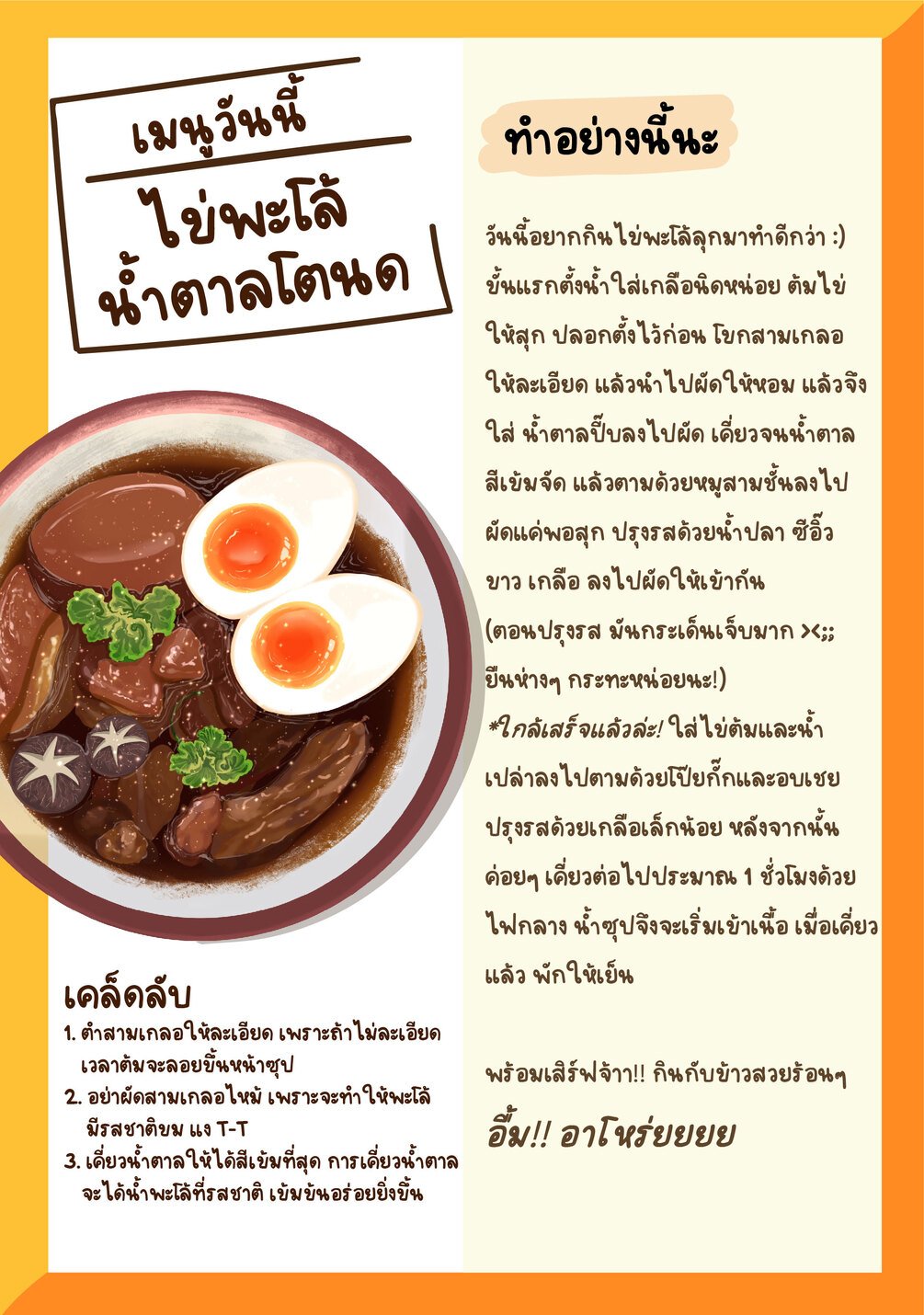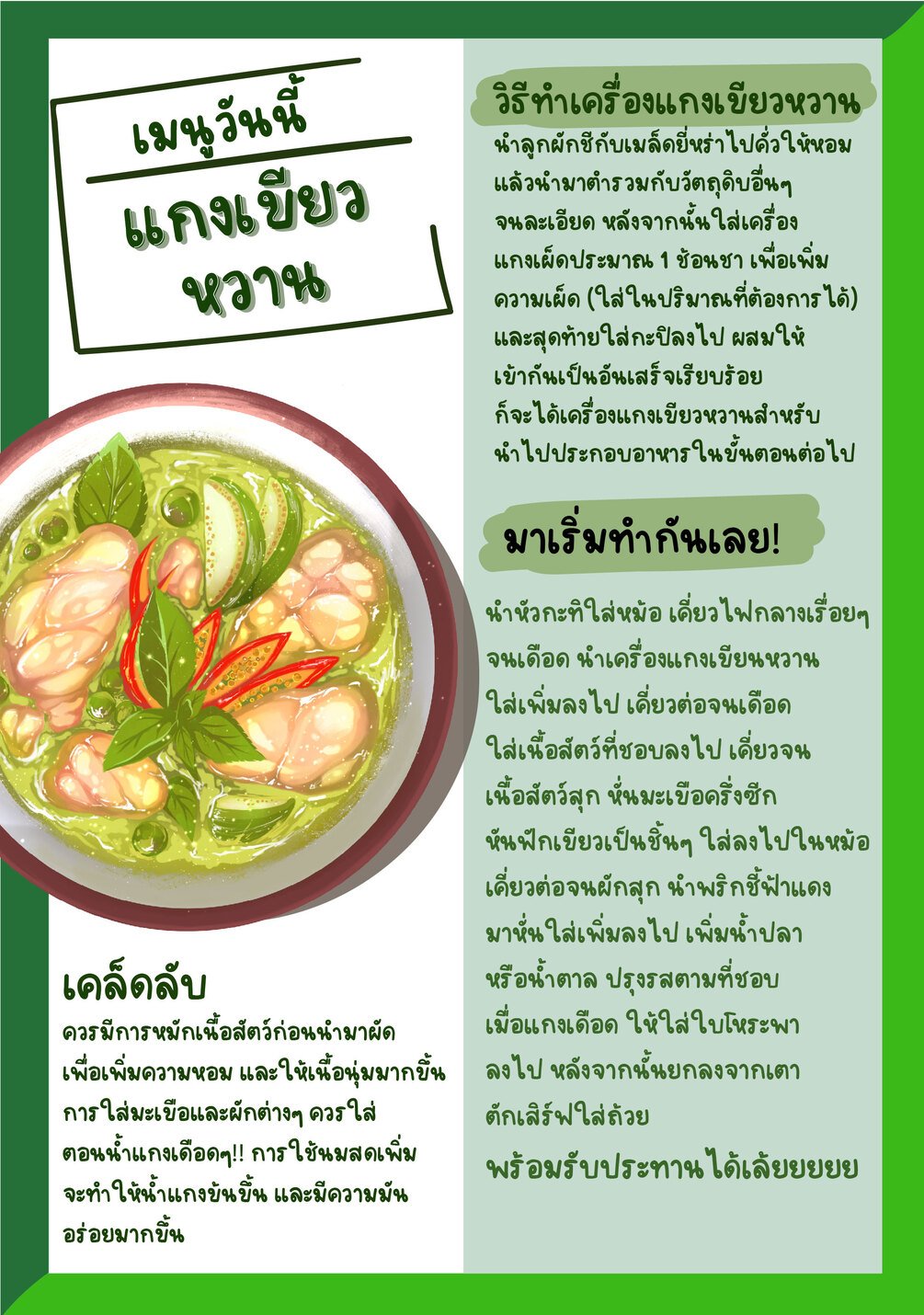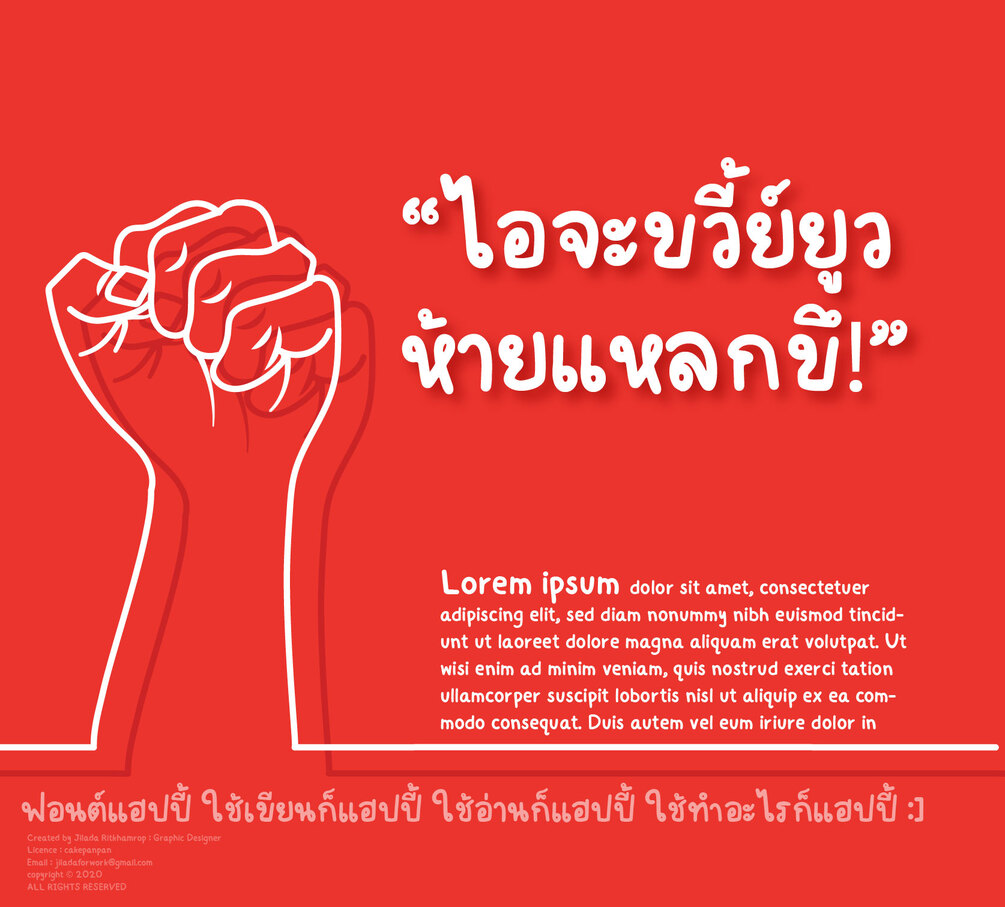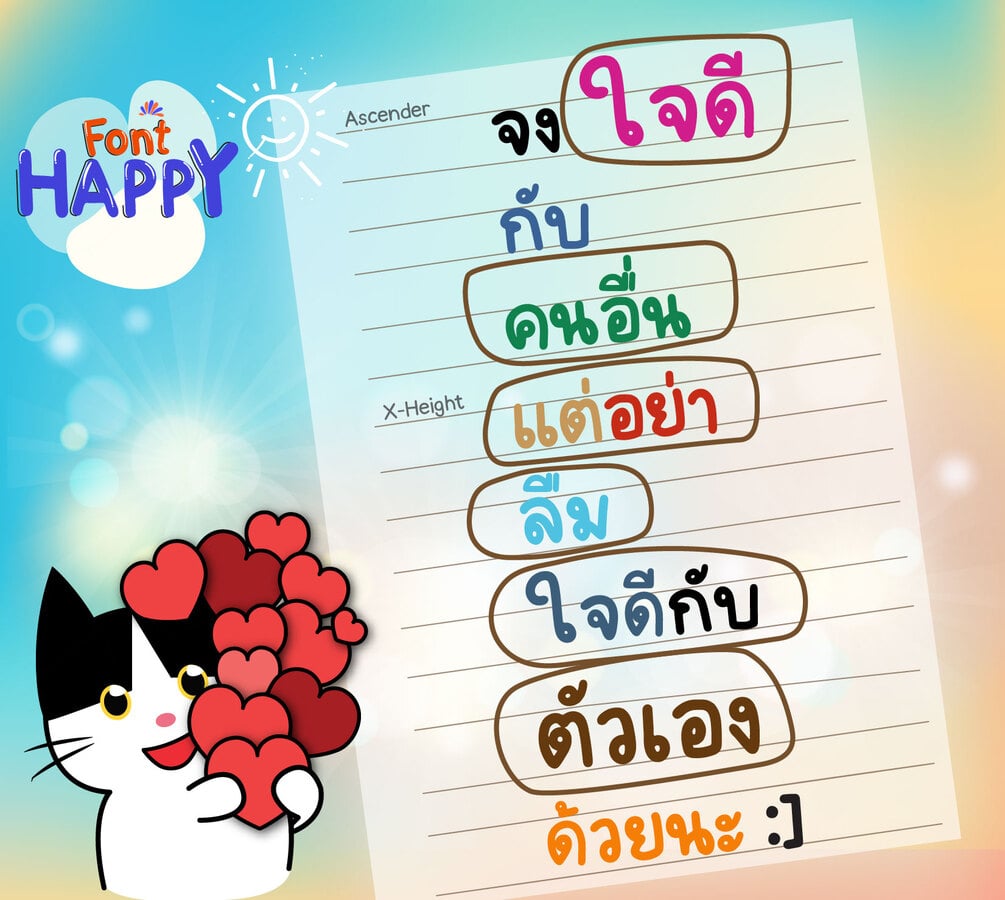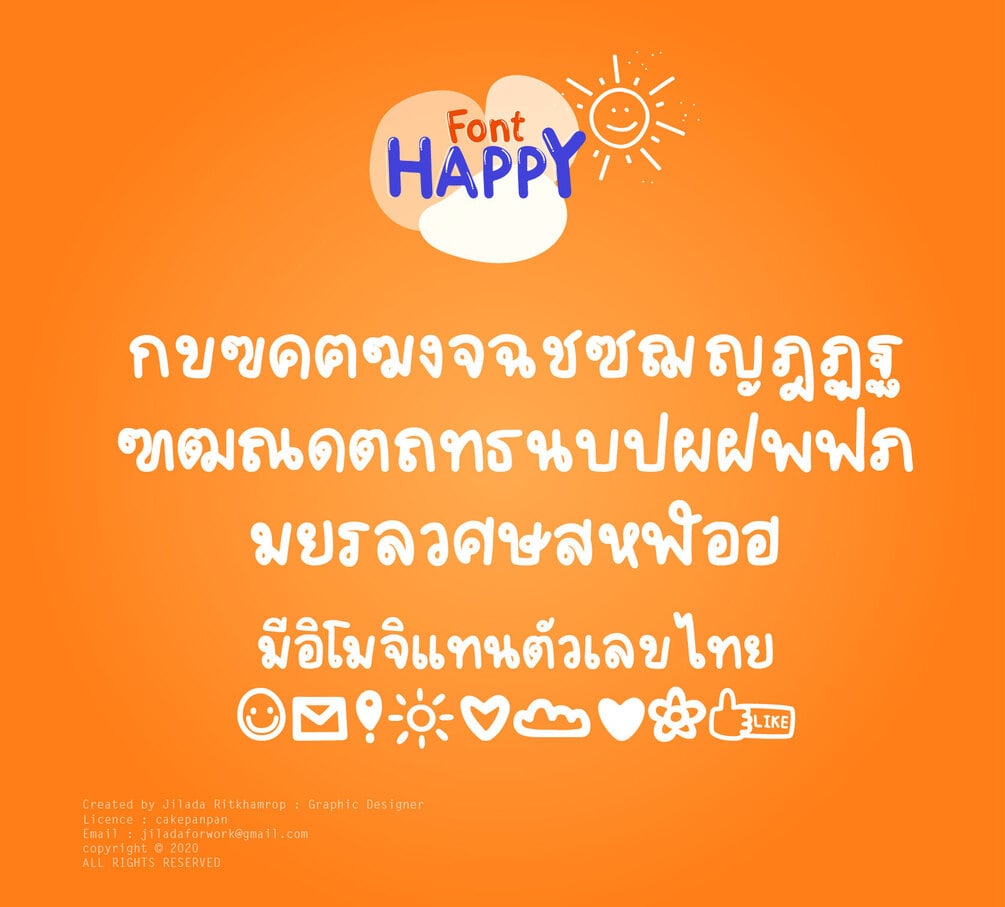
Happy Font (ฟอนต์แฮปปี้)
ชื่อฟอนต์แฮปปี้ เพราะอยากให้ทุกคนแฮปปี้ ^____^
ท่ามกลางวิกฤตอะไรก็ตาม ขอแค่ตัวเรายิ้มให้กับทุกปัญหา แล้วเราจะบ้าไปเองจ้าาา~
ฟอนต์ตัวนี้มีอิโมจิแทนตัวเลขไทยนะคะ ใช้จดโน้ตน่ารักสุดๆ ไปเลยค้าบบ ><